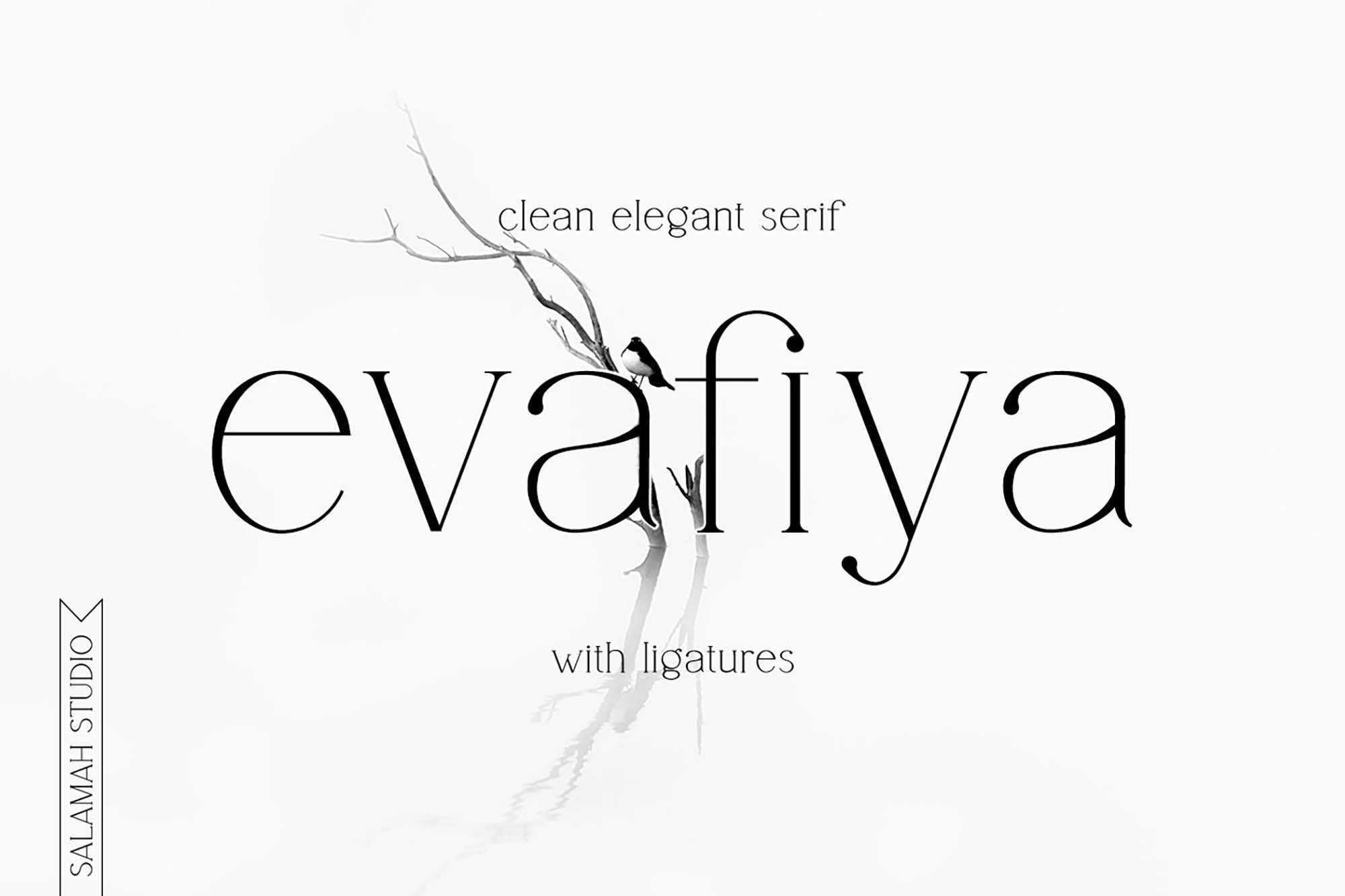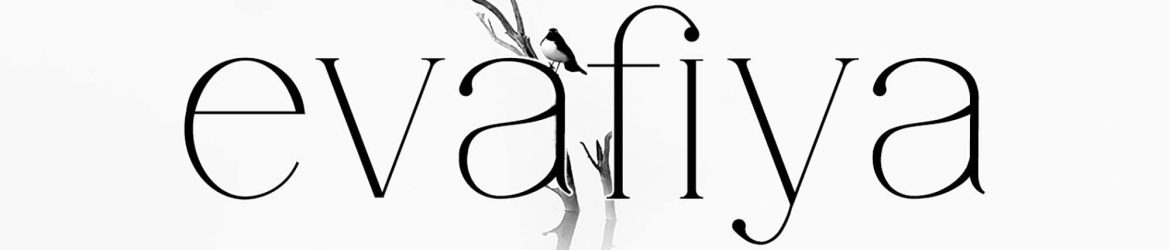
A Evafiya Serif é uma fonte elegante e sofisticada, perfeitamente adaptada para design de alta qualidade. Ainda que existam milhões de fontes disponíveis, a Evafiya está projetada para atender a necessidades de design formal, tradicional e elegante. Esta fonte é ideal para quem busca um toque de elegância em seus projetos, seja para logotipos de marca, materiais de marketing ou qualquer outra aplicação gráfica. A fonte Evafiya é uma seleção perfeita para aqueles que desejam um ar de sofisticação em seus designs, com seu estilo elegante e harmonioso que complementa qualquer tema, garantindo um impacto significativo em qualquer projeto.